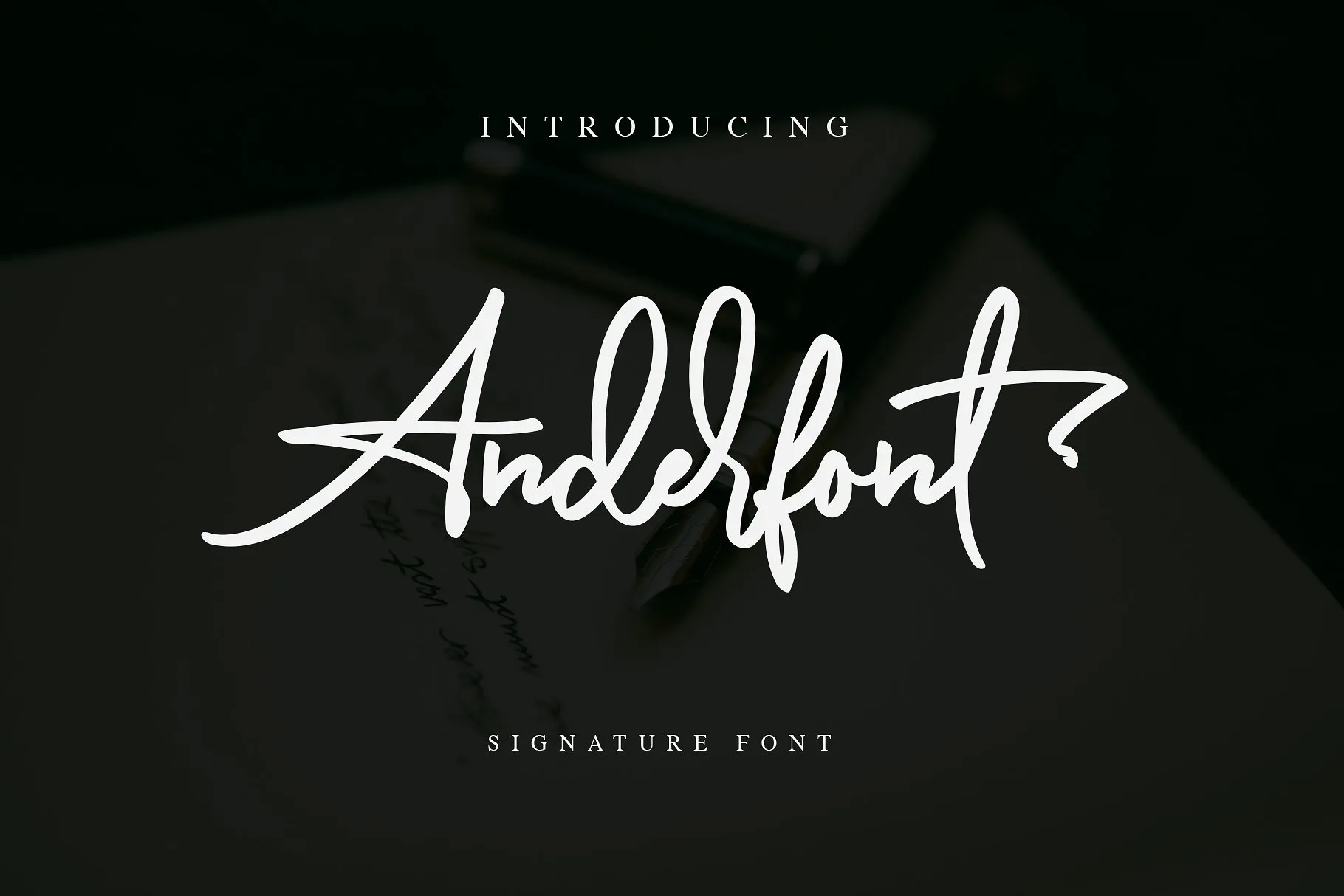
Anderfont Signature Font – Download Grátis
A Anderfont Signature Font é uma elegante tipografia feita a mão que inclui ligaturas para um aspecto totalmente autêntico e criativo em seus projetos. Esta fonte, pertencente à categoria de Script Fonts, traz um toque sofisticado com sua escrita limpa e versátil, adequada para uma variedade de aplicativos como logotipos de firma, assinaturas, capas de álbum, cartões de visita ou até mesmo como marcas em fotos. Essa font é uma excelente adição para qualquer designer que procura tornar seus trabalhos ainda mais profissionais e originais. Com sua estrutura minimalista e atraente, Anderfont Signature é perfeita para aqueles projetos que exigem um certo toque de elegância contemporânea. Seja você uma agência de marketing ou artesãos digitais, Anderfont pode ser o elemento chave para dar um novo impulso à sua identidade visual e a qualidade do seu trabalho. Com certeza, esta font vai encorajar os criativos a elevarem seus projetos a novos patamares de sofisticação e originalidade.